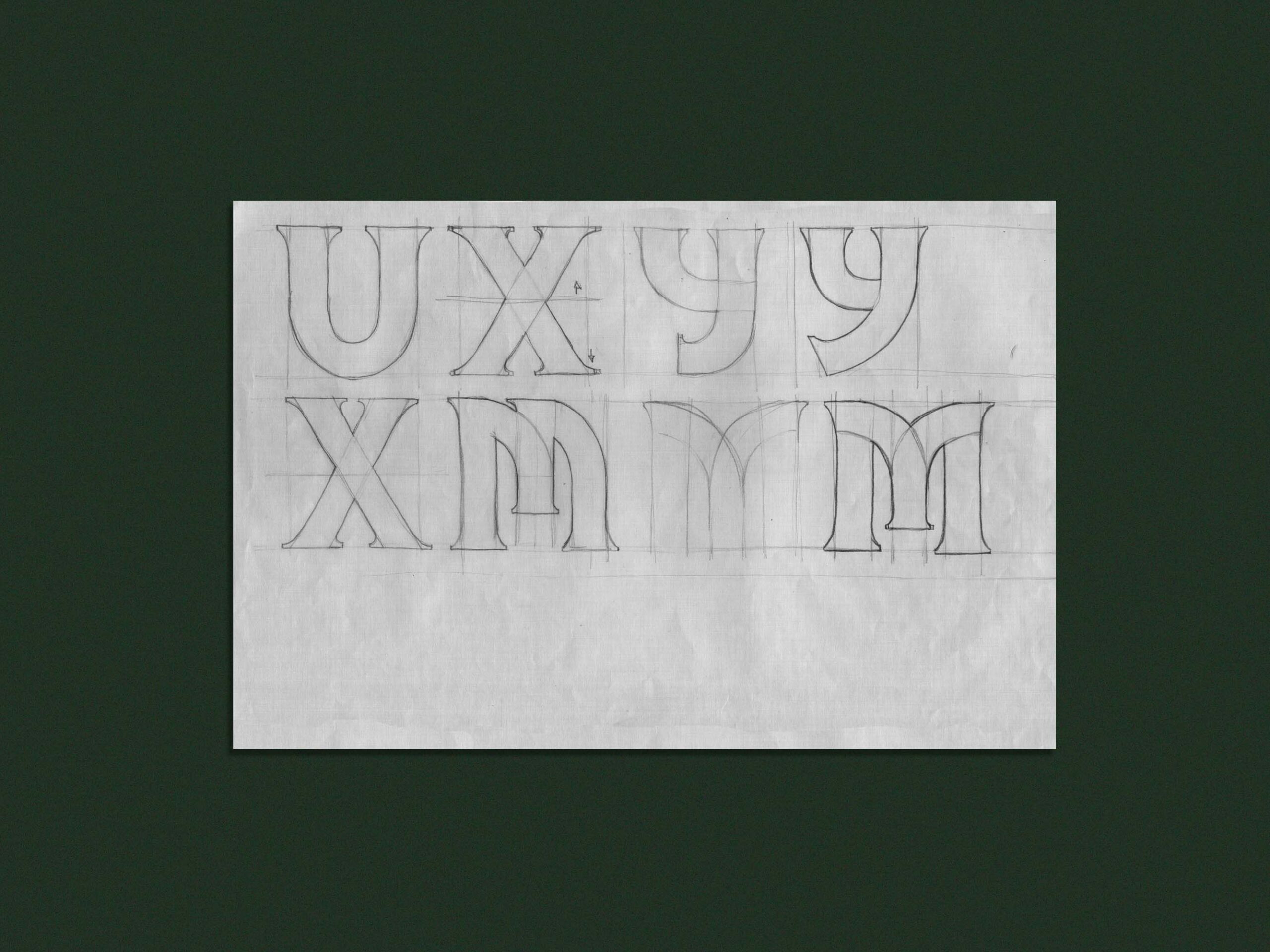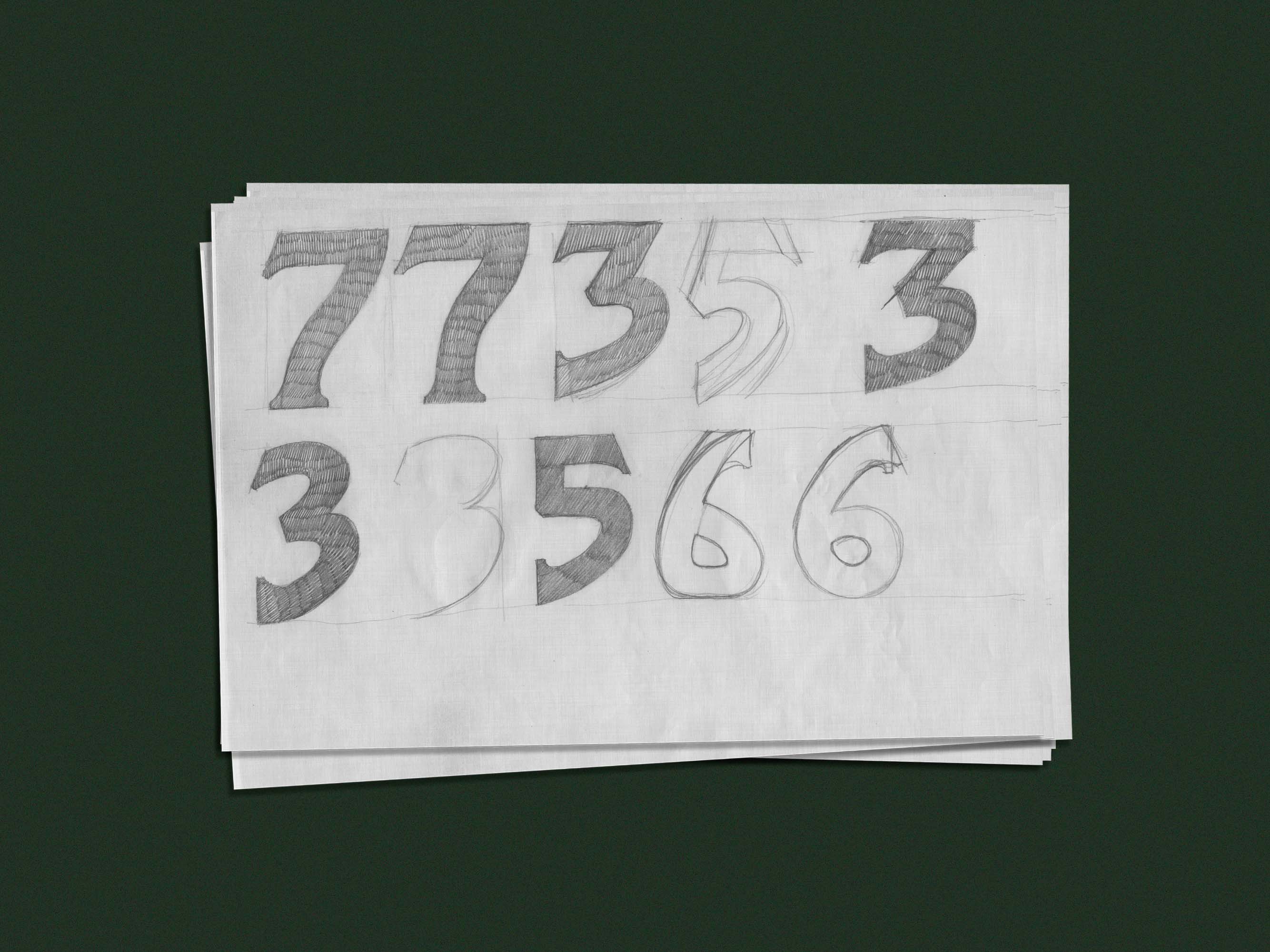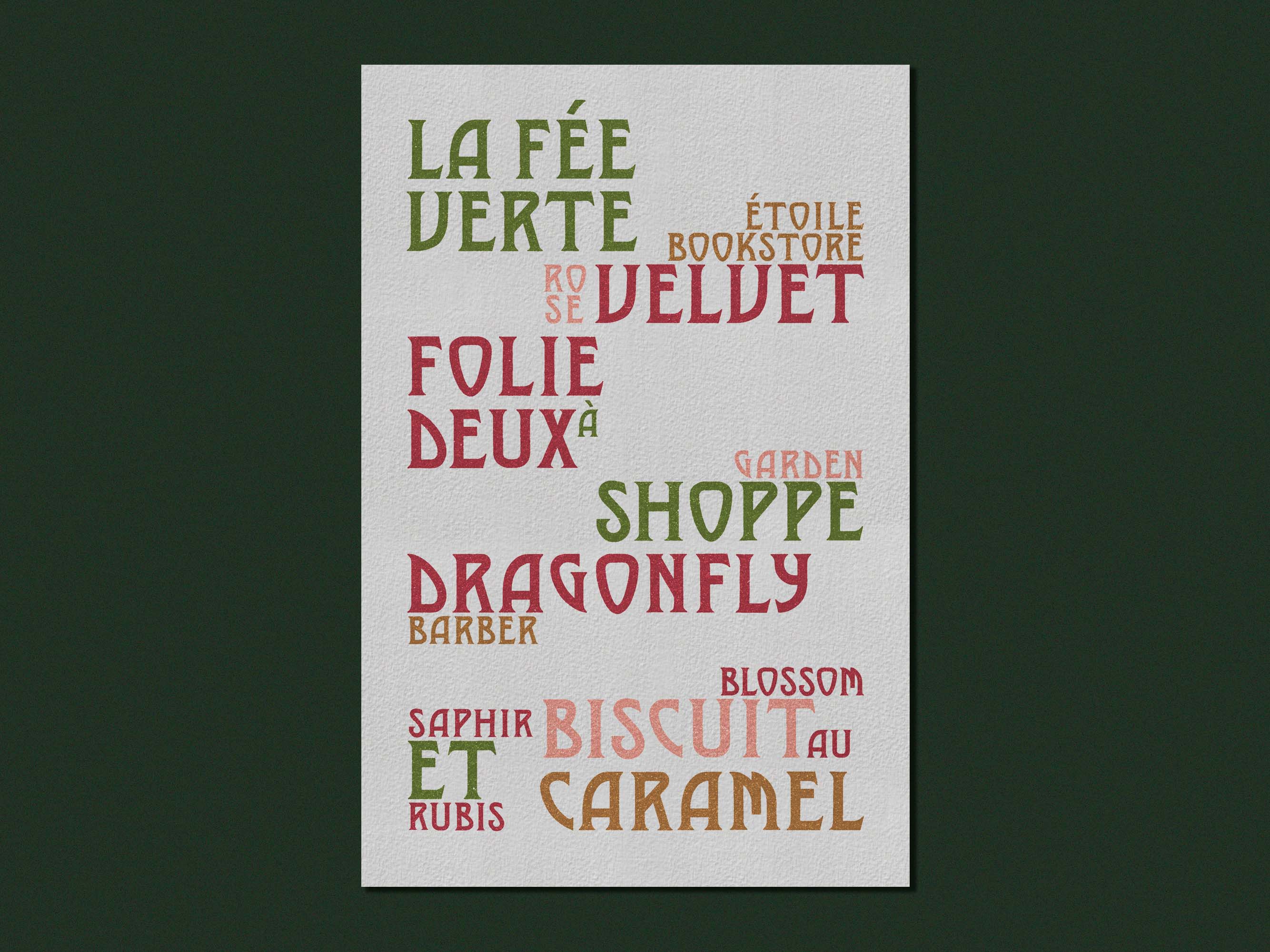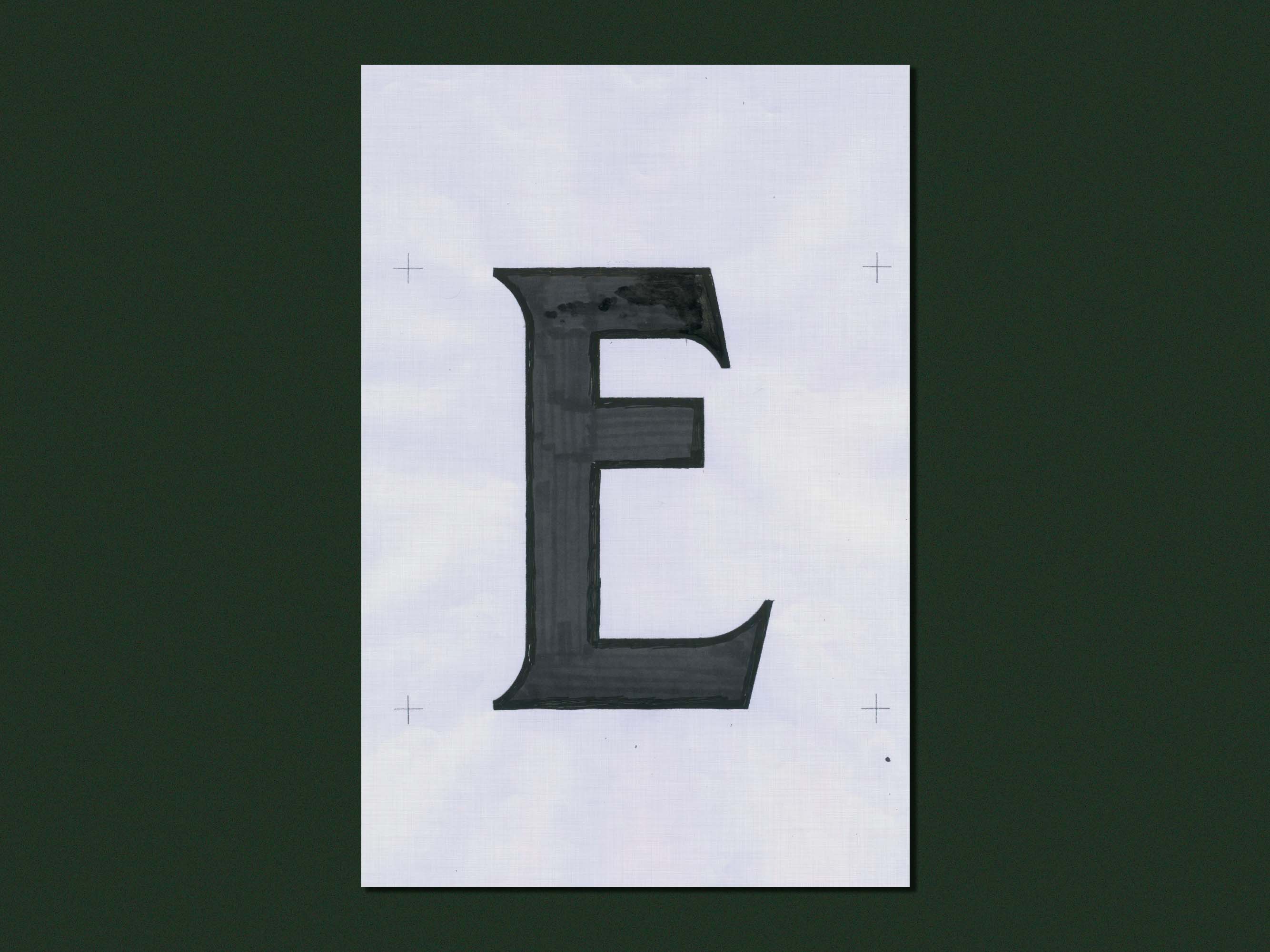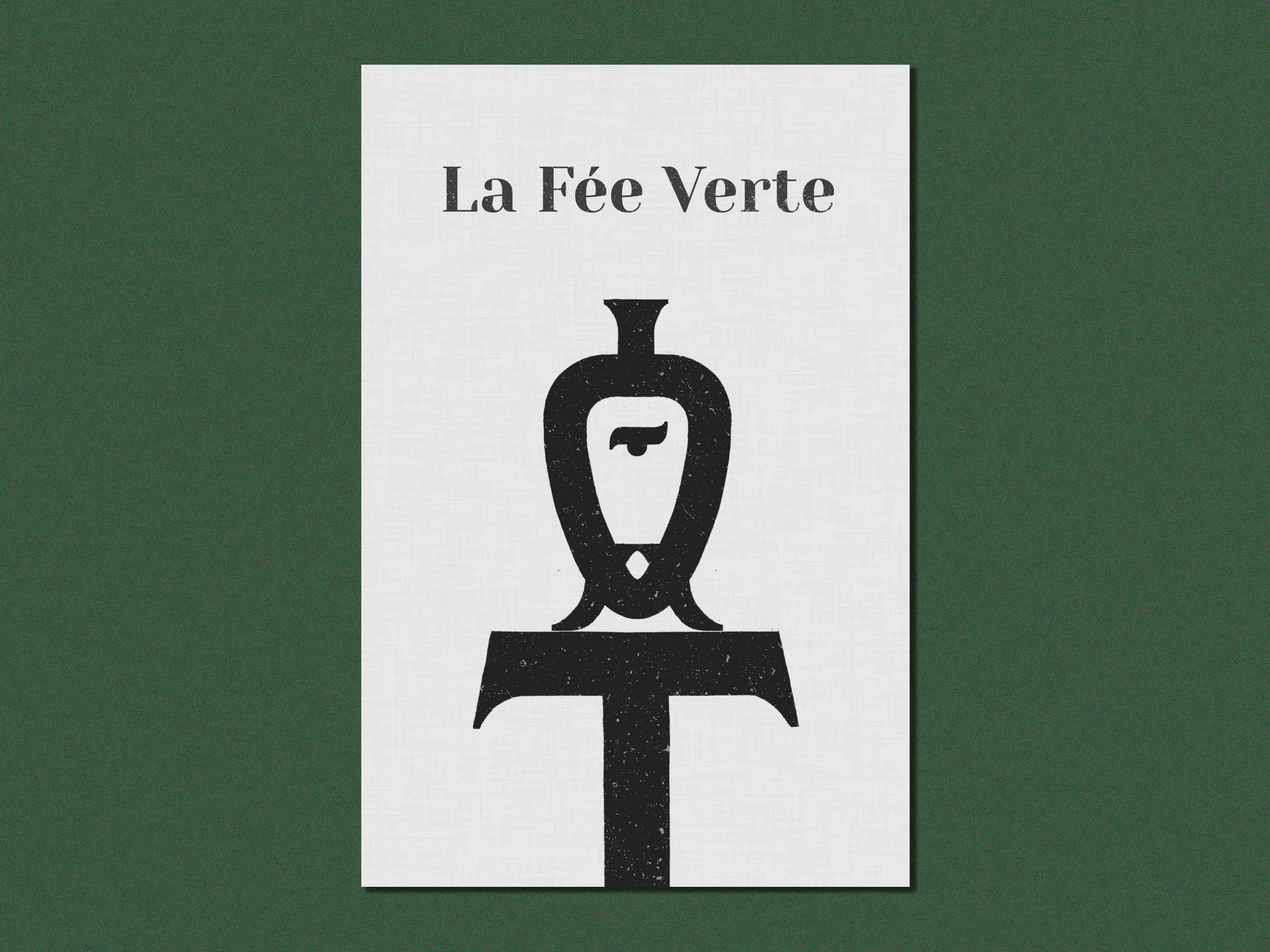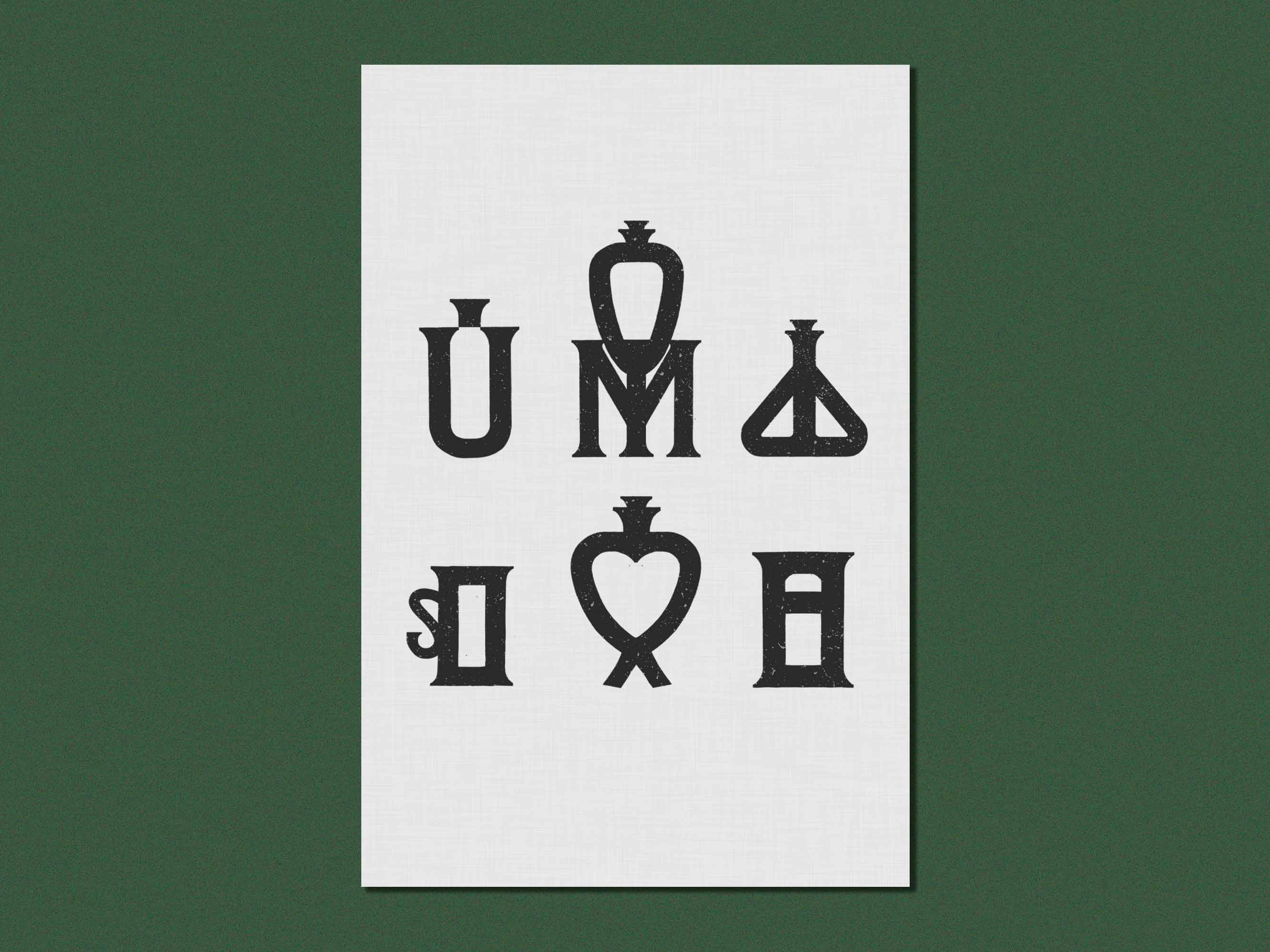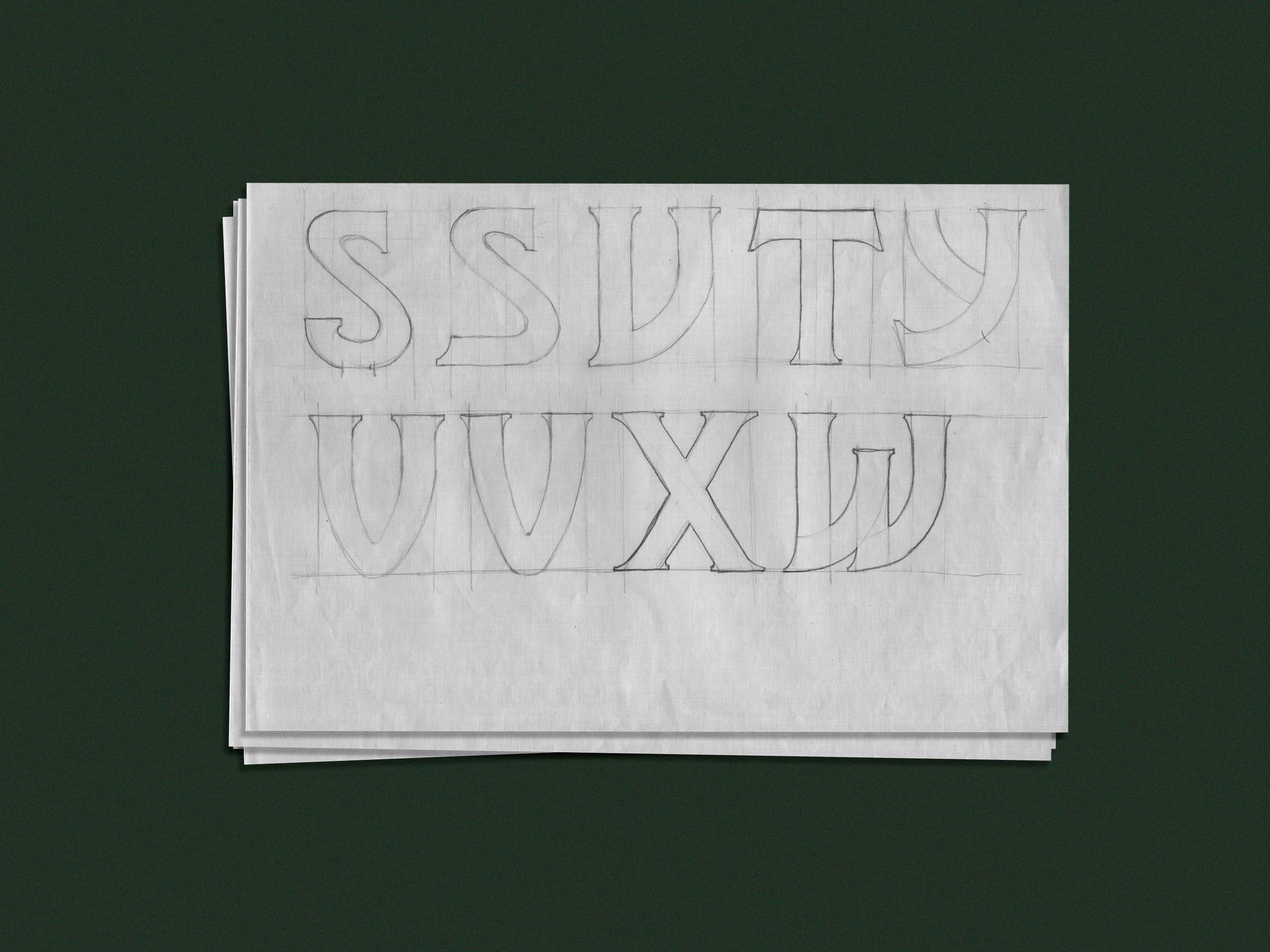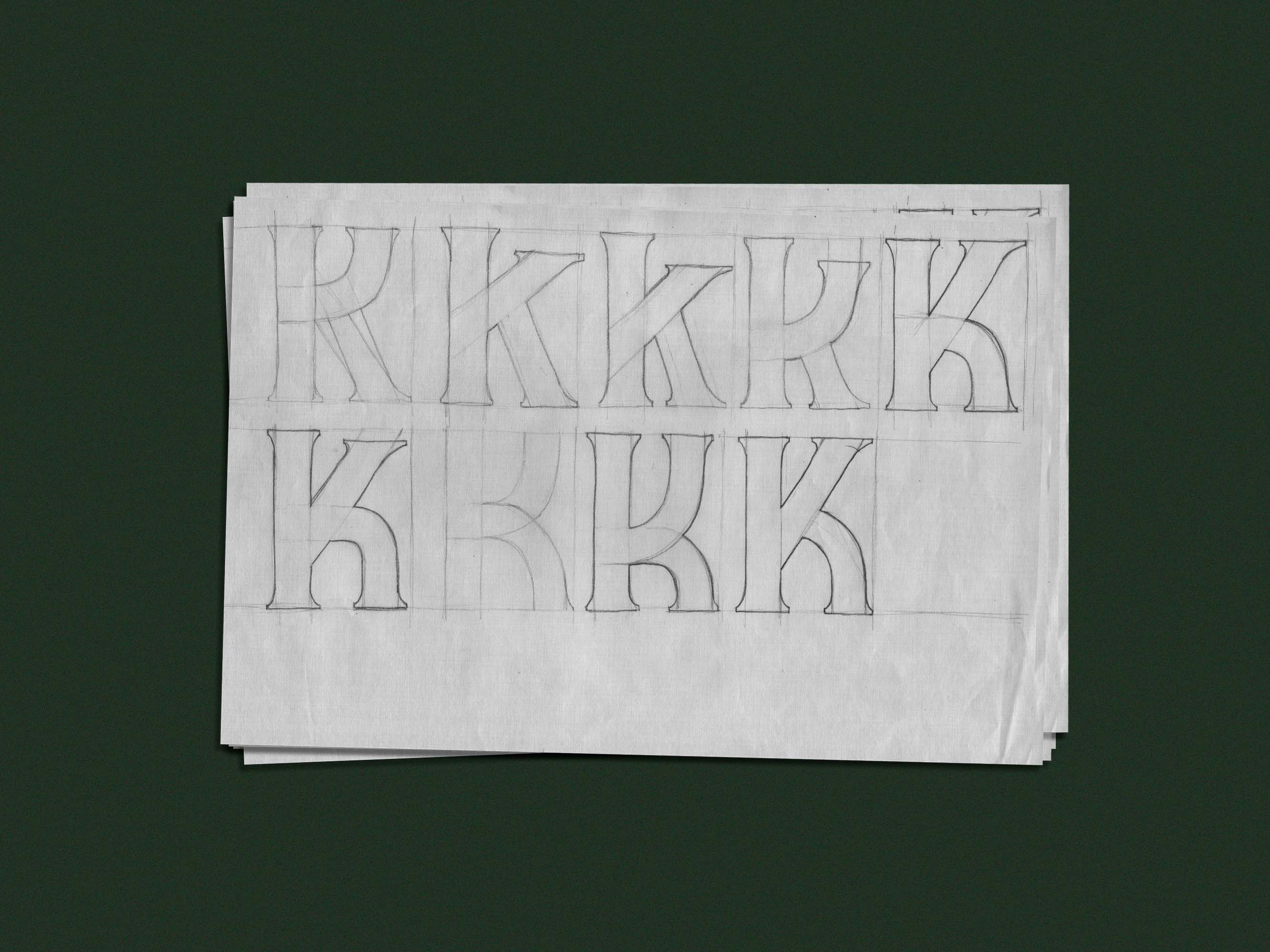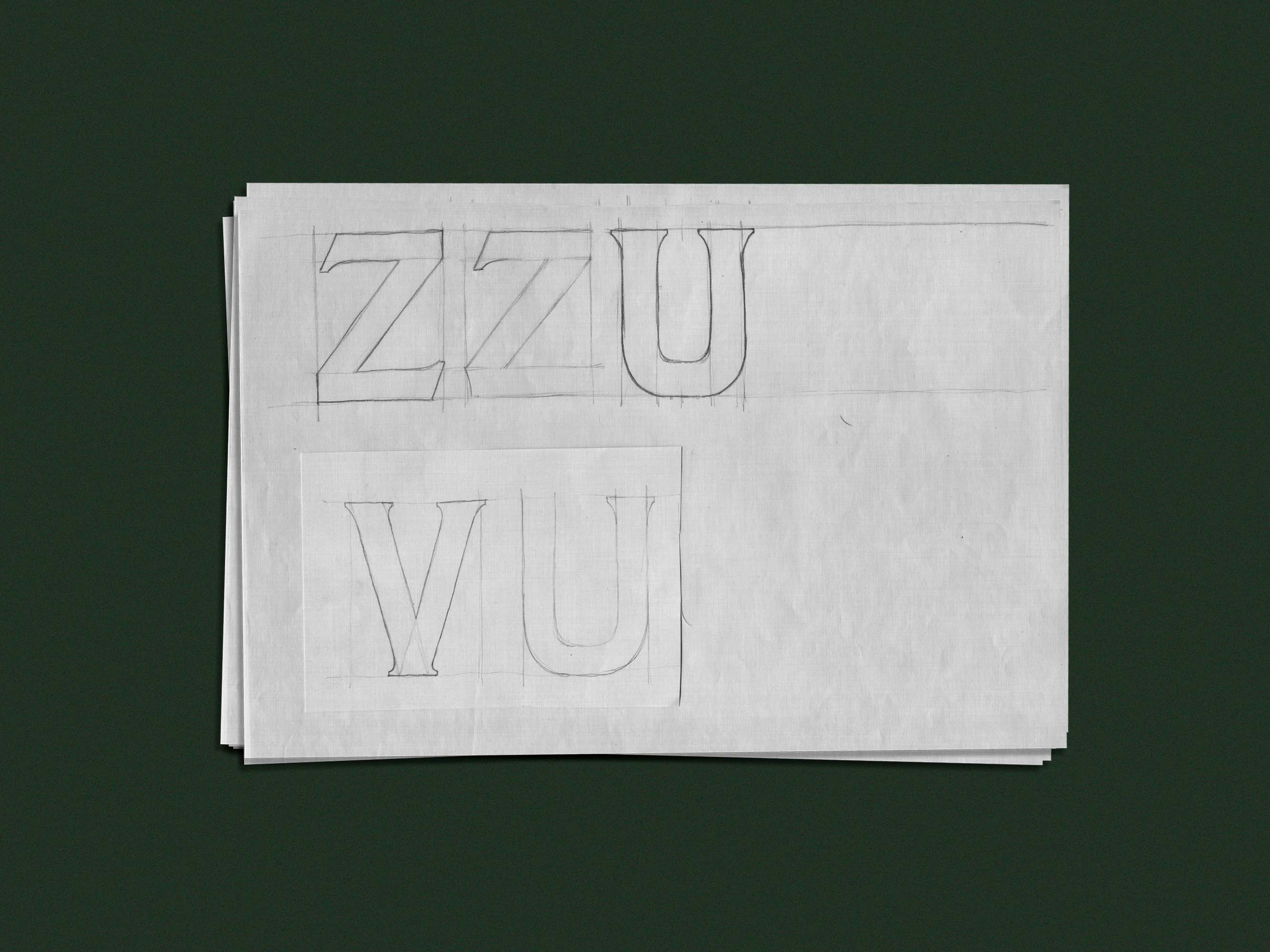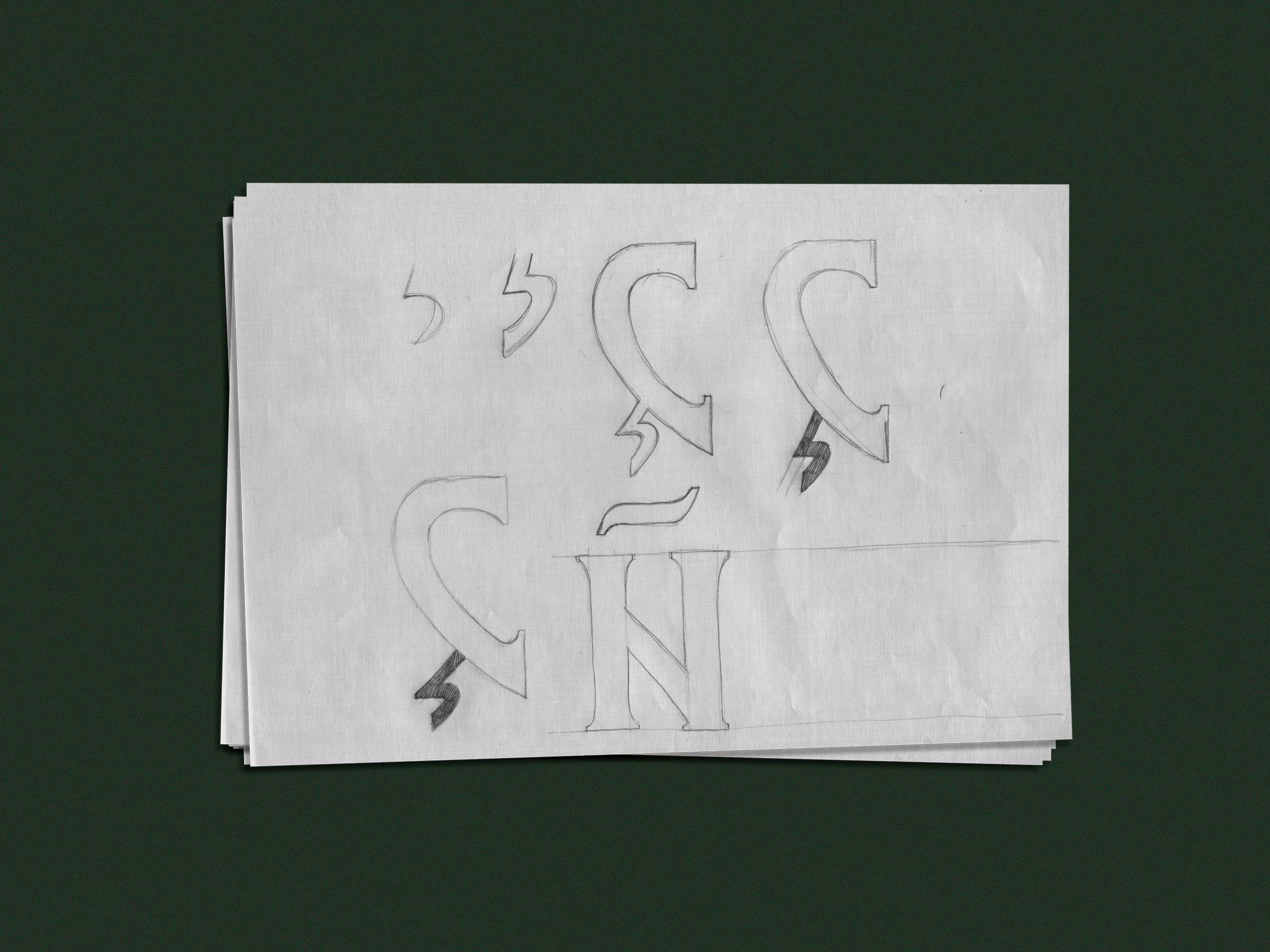
Font La Fée Verte
La Fée Verte è stata progettata partendo dal recupero di una font da titolazione della fonderia Augusta, dai tipi in legno. La progettazione di ogni lettera ha seguito il decorso analogico composto da schizzi, bozzetti, riempimento, tutto a mano libera. Ad oggi è in fase di digitalizzazione.